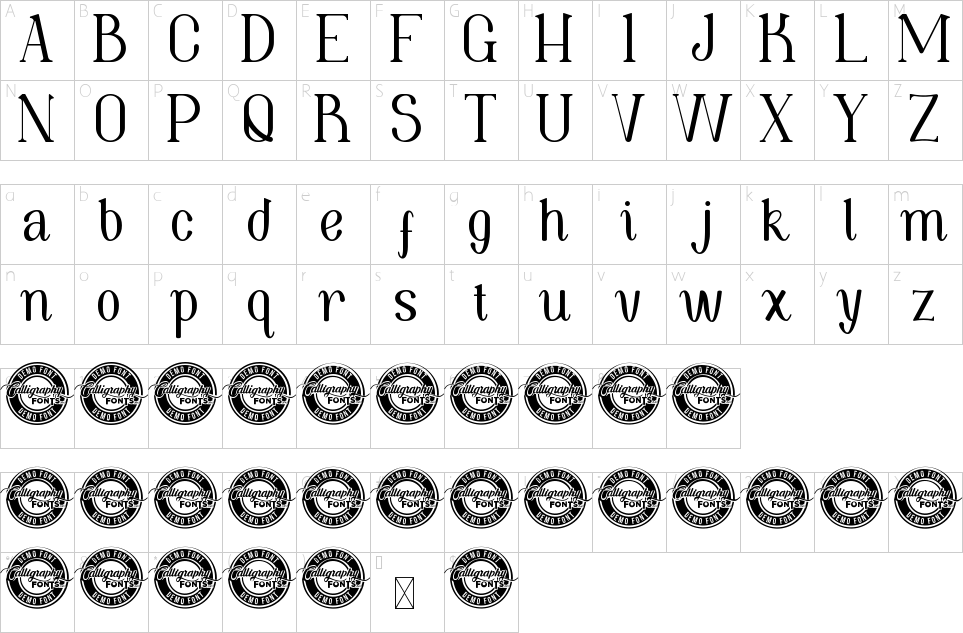
A Mazy Theory é uma fonte elegante e versátil criada por CalligraphyFonts. Esta fonte oferece um estilo minimalista e moderno, ideal para diversas aplicações, desde rótulos de embalagens até editoriais digitais. Com seu design cuidadosamente elaborado, a Mazy Theory oferece legibilidade superior e um ar de sofisticação. O fato de ser de graça faz com que esta fonte seja especialmente atraente para designers que procuram novas opções sem comprometer seus orçamentos. Recentemente, mais de 3.269 pessoas já experimentaram e aderiram à simplicidade e elegância da Mazy Theory. Se você está procurando uma fonte que combine elegância com praticidade, a Mazy Theory é um excelente ponto de partida.